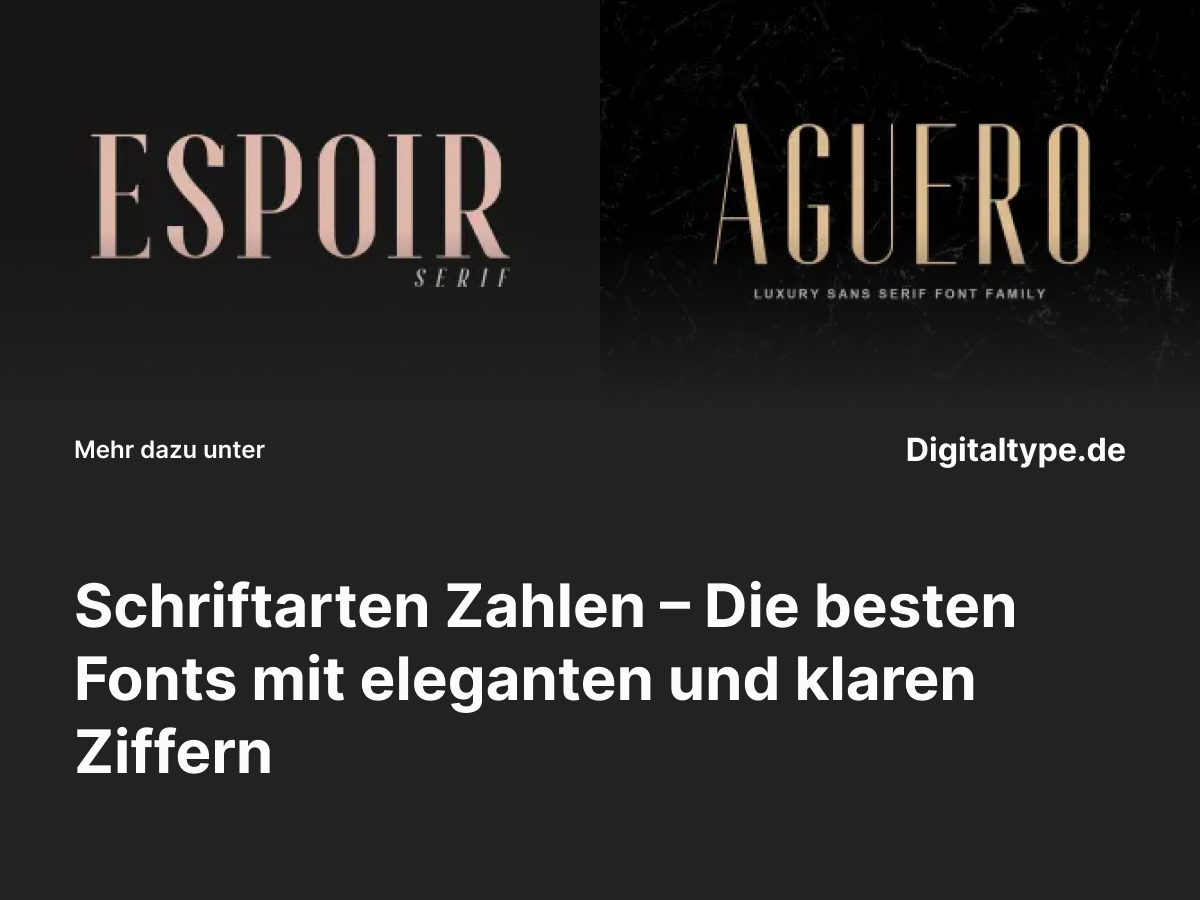
Wenn du ein Design erstellst, spielen nicht nur Buchstaben, sondern auch Zahlen eine entscheidende Rolle. Ob für Preisangaben, Kalender, Uhrzeiten oder Infografiken – die Wahl der richtigen Schriftart mit schönen Zahlen sorgt für Lesbarkeit, Harmonie und Stil.
In diesem Artikel erfährst du, was gute Zahlenschriften auszeichnet und welche eleganten Font-Alternativen sich besonders für professionelle Designs eignen.
Was sind Schriftarten mit schönen Zahlen?
Unter Schriftarten Zahlen versteht man Fonts, deren Ziffernformen mit besonderer Sorgfalt gestaltet wurden. Sie sind gleichmäßig, harmonisch und passen sich perfekt an die Buchstabenästhetik der Schrift an.
In hochwertigen Typografien sind die Zahlen nicht nur funktional, sondern ein wesentliches Designelement – vor allem in Logos, Magazinen oder luxuriösen Markenauftritten.
Designer achten besonders darauf, dass Ziffern optisch ausbalanciert sind. So wirken Preisangaben, Überschriften oder Tabellen professioneller und ästhetischer. Eine passende Schriftart für Zahlen kann deinem Design einen raffinierten, edlen Touch verleihen.
Wann du Schriftarten mit schönen Zahlen verwenden solltest
- 1. In Logos und Branding-Projekten: Für Marken mit Zahlen im Namen oder Gründungsjahr (z. B. „Studio 88“ oder „Since 1985“).
- 2. In Editorial-Designs: Wenn Ziffern in Überschriften, Tabellen oder Seitenzahlen eine gestalterische Rolle spielen.
- 3. In luxuriösen Layouts: Besonders in Magazinen, Modekatalogen oder Corporate Designs für Premium-Marken.
- 4. Für Packaging oder Preisgestaltung: Damit Zahlen edel und professionell wirken.
Eine Schriftart mit schönen Zahlen vereint Lesbarkeit, Stil und Balance – ideal für Designer, die Wert auf jedes Detail legen.
Die 6 besten Schriftarten mit schönen Zahlen
Hier sind sechs ausgewählte Schriftarten Zahlen, die Eleganz, Professionalität und typografische Präzision kombinieren. Perfekt für Branding, Editorials und kreative Projekte mit Stil.
1. Espoir Serif Font Family
Espoir ist eine elegante Serifenschrift mit fein ausgearbeiteten Zahlenformen. Ihre Balance aus Klassik und Moderne macht sie perfekt für Branding und Printdesigns. Besonders geeignet für Logos oder Magazine mit luxuriösem Look.
2. Aguero Serif – Clean Elegant Font
Aguero überzeugt durch klare Linien und harmonische Proportionen. Die Ziffern sind gleichmäßig, stilvoll und ideal für Designs, die Präzision und Eleganz erfordern – etwa Uhrenmarken, Corporate Design oder Packaging.
3. Riffle Font Family
Riffle ist eine moderne Serifenschrift mit markanten Details. Ihre Ziffern sind besonders klar und gut lesbar, was sie zur idealen Wahl für Tabellen, Editorials oder Business-Kommunikation macht.
4. Coldiac Luxury Serif Font
Coldiac bringt Luxus und Raffinesse in jedes Design. Die Zahlen sind elegant proportioniert und passen perfekt zu hochwertigen Layouts – ideal für Mode, Schmuck oder Premium-Marken mit Sinn für Stil.
5. Gold Coast Vintage Serif Font Family + Extras
Gold Coast kombiniert klassischen Charme mit Vintage-Flair. Ihre Zahlen wirken nostalgisch, aber dennoch elegant – perfekt für Retro-Projekte, Weinlabels oder Branding mit zeitlosem Charakter.
6. Belgium Font Family
Belgium ist eine stilvolle Serifenschrift mit modernem Charakter. Ihre klaren, ausgewogenen Zahlen machen sie ideal für Corporate Designs, Printmedien und Branding, das Vertrauen und Professionalität ausstrahlt.
Design-Tipps für Schriftarten mit Zahlen
- 1. Verwende proportionale Ziffern: Sie sorgen für ein harmonisches Schriftbild in Fließtexten.
- 2. Nutze Versalziffern in Logos: Sie wirken klassischer und edler als Mediävalziffern.
- 3. Teste unterschiedliche Größen: So stellst du sicher, dass Zahlen in jedem Format gut lesbar bleiben.
- 4. Kombiniere mit klaren Sans-Serif-Fonts: Für ein modernes, professionelles Gesamtbild.
Fazit: Elegante Zahlen-Schriftarten für stilvolle Designs
Eine Schriftart mit schönen Zahlen bringt Professionalität, Stil und visuelle Harmonie in dein Design. Ob du eine elegante Serifenschrift oder eine moderne Variante bevorzugst – die richtige Wahl sorgt dafür, dass jedes Detail perfekt wirkt.
Die hier vorgestellten Fonts zeigen, wie vielfältig Zahlen in der Typografie sein können – von klassisch-edel bis modern-minimalistisch. Probiere sie in deinen Projekten aus und verleihe deinen Designs den letzten Schliff.